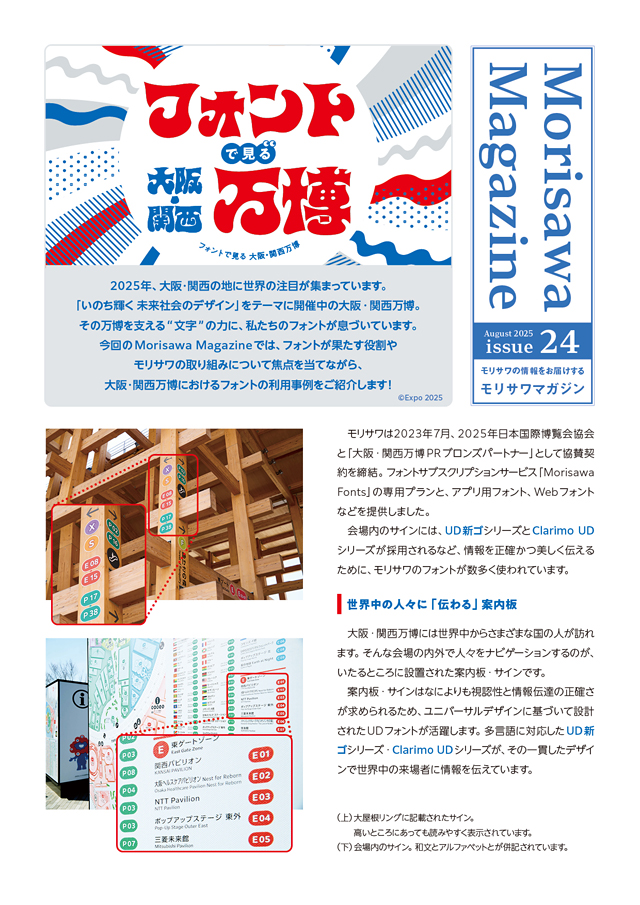
MORISAWA MAGAZINE 2025年24号 ダウンロード フォントで見る大阪・関西万博 本号は、大阪・関西万博で使用されているフォントについて特集しています。大屋根リングや案内板で使われているフォント、各パビリオンでその世界観を表現するフォントなど、フォントが果たす役割やモリサワの取り組みについて焦点を当てながら、利用事例をご紹介します。 一覧に戻る